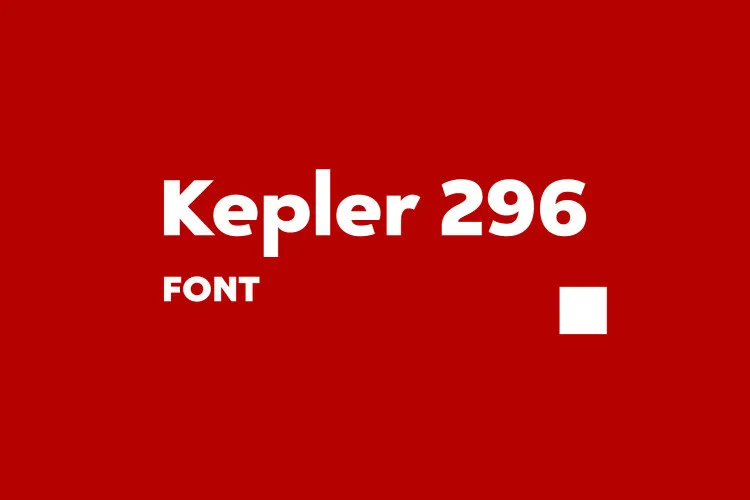
A fonte “Kepler 296 Sans” é uma elegante tipografia sans-serif compacta criada por Igor Kosinsky. Esta fonte experimental é especialmente indicada para projetos onde você deseja destacar suas ideias ou criar conteúdo visualmente impactante. É ideal tanto para criação de posters inovadores quanto para desenvolvimento de conteúdos sociais, logotipos, projetos impressos e muito mais. Suportando caracteres latino e cirílico amplamente, a “Kepler 296 Sans” é extremamente versátil, tornando-a uma excelente adição a qualquer projeto que você possa ter em mente. Seja para criar um design único ou trabalhar com conteúdo social, a “Kepler 296 Sans” certamente se destacará, oferecendo um toque moderno e arrojado ao seu trabalho gráfico.